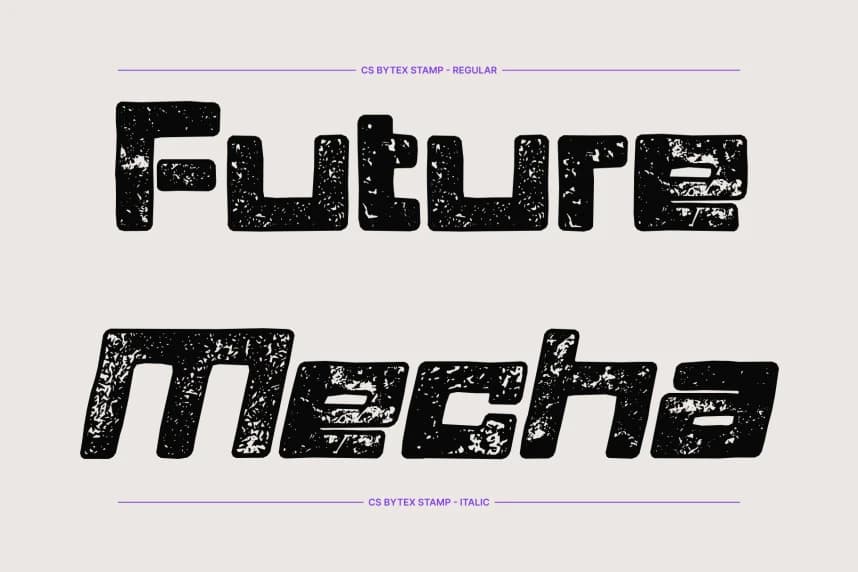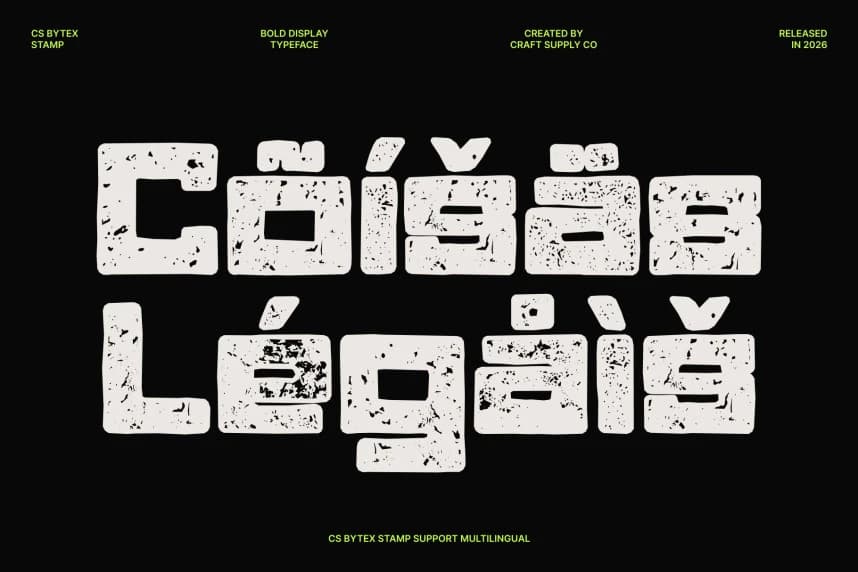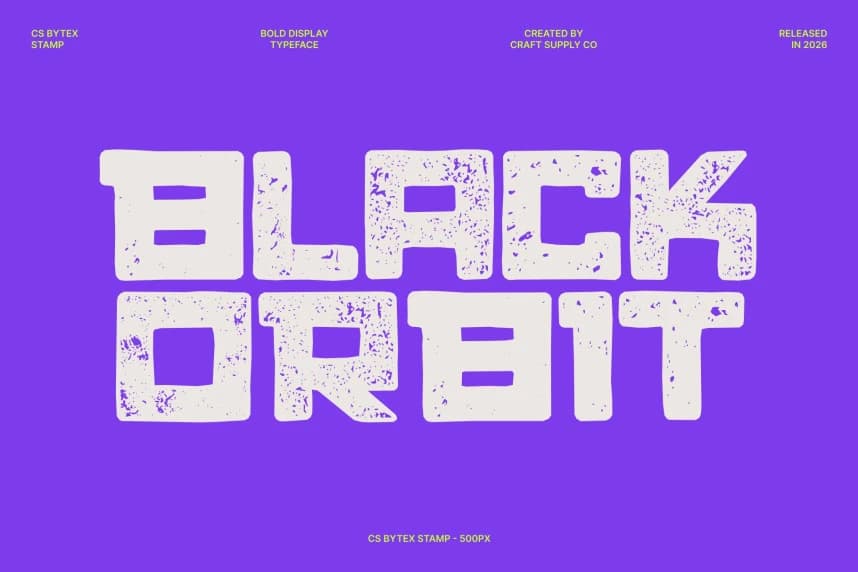
CS Bytex Stamp Font
CS Bytex Stamp Font – Vintage Dokuya Sahip Cesur Dijital Yazı Tipi; Fütüristik Sans Serif, El Yapımı Damga Estetiğiyle Buluşuyor. Bu, vintage damga etkisiyle yeniden tasarlanmış cesur, teknoloji esintili bir sans serif fontudur.
CS Bytex Stamp Font – Vintage dokulu kalın dijital yazı tipi, Gelecekçi Sans Serif ile El Yapımı Damga Estetiğinin Buluşması. Bu, kalın, teknoloji esintili bir sans serif yazı tipinin vintage damga etkisiyle yeniden tasarlanmış halidir.